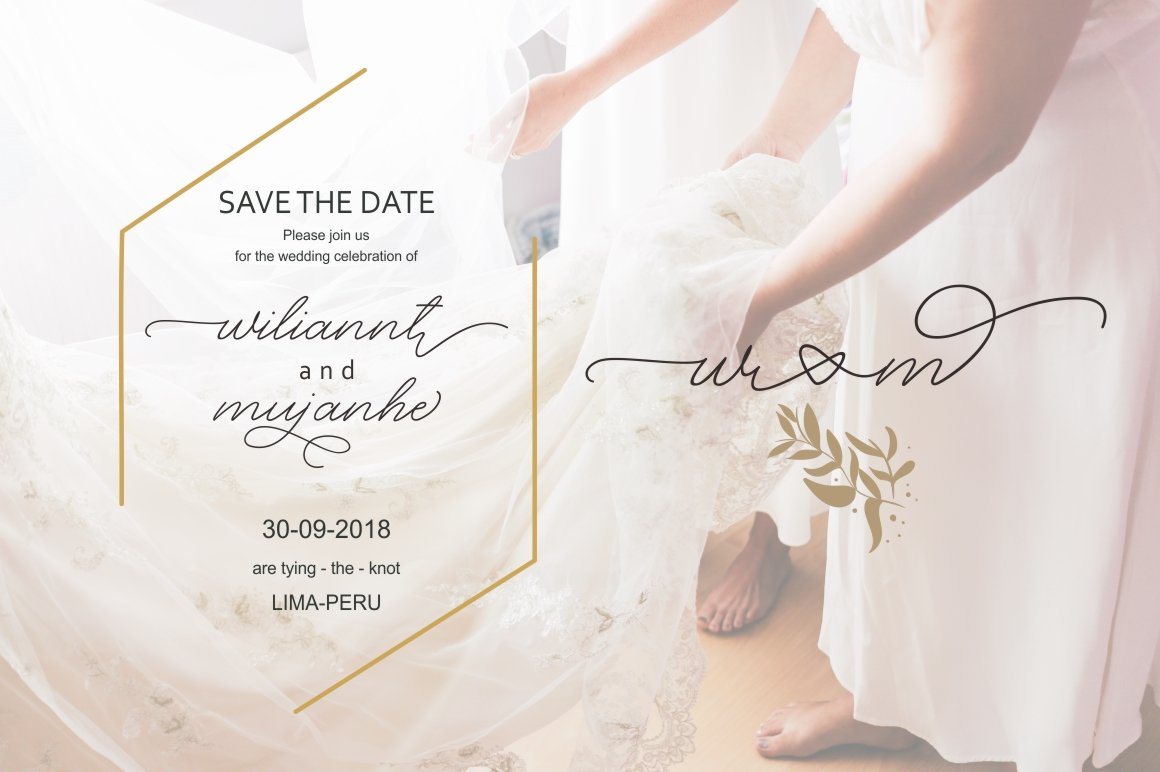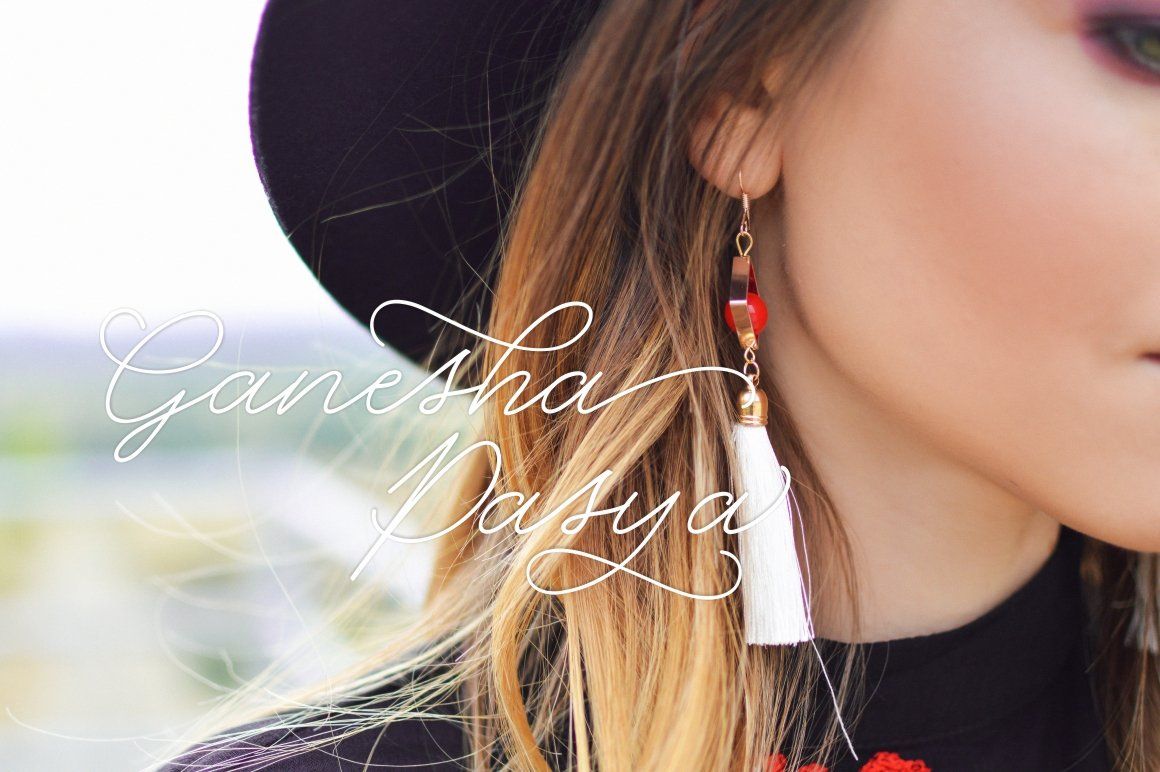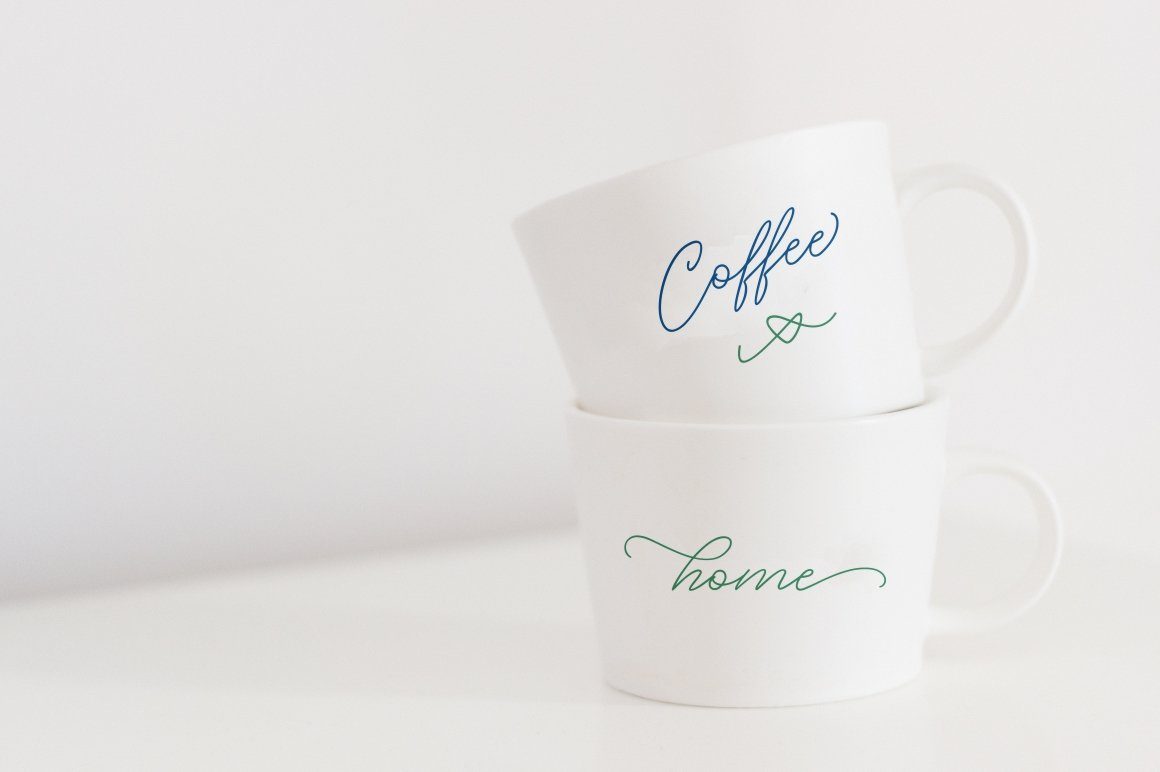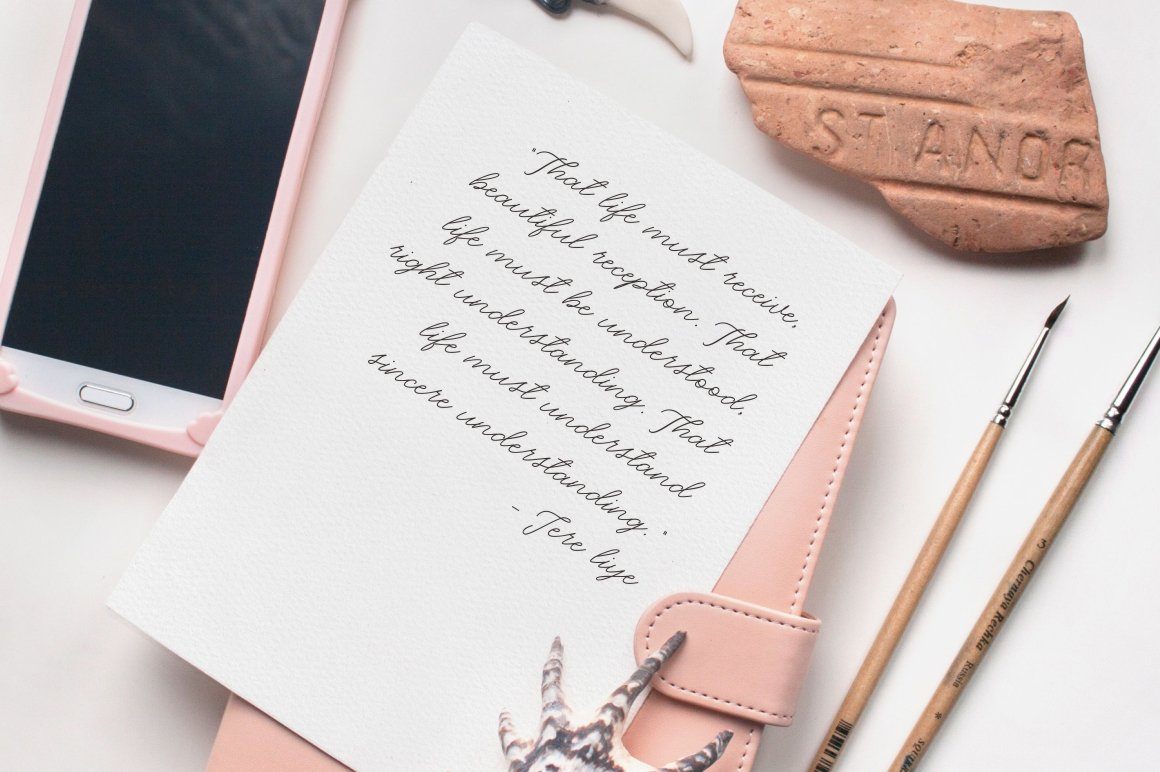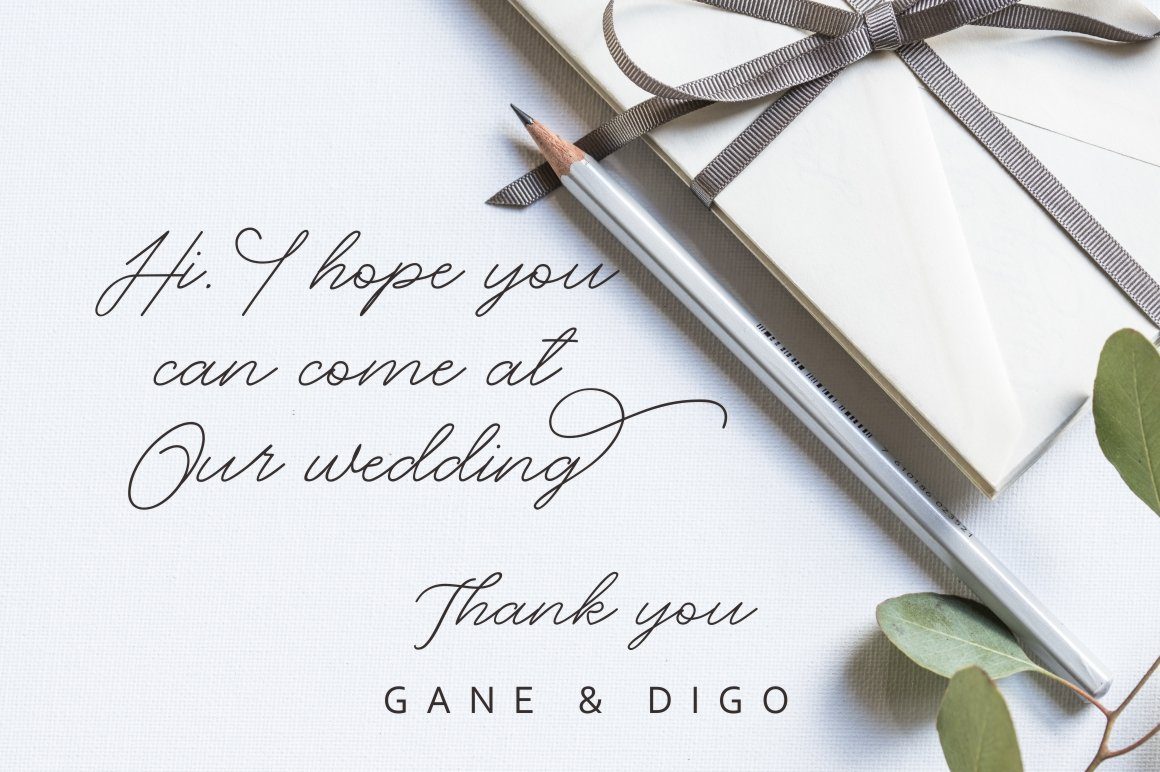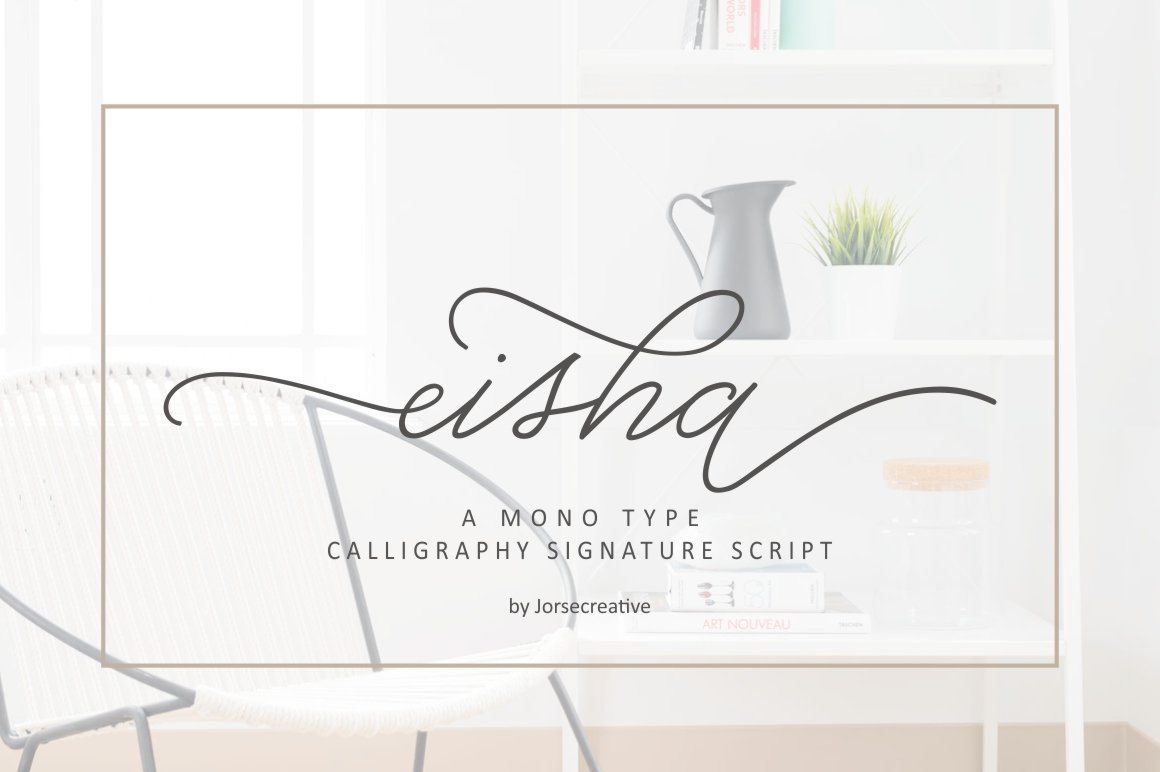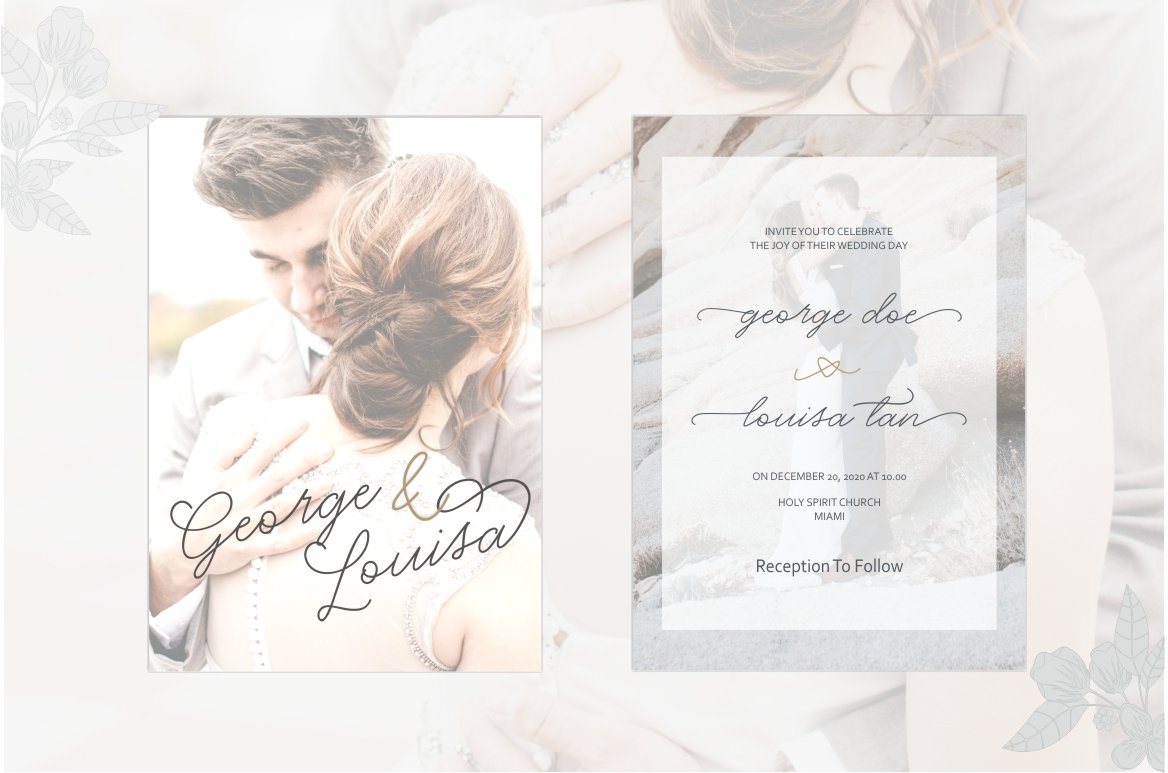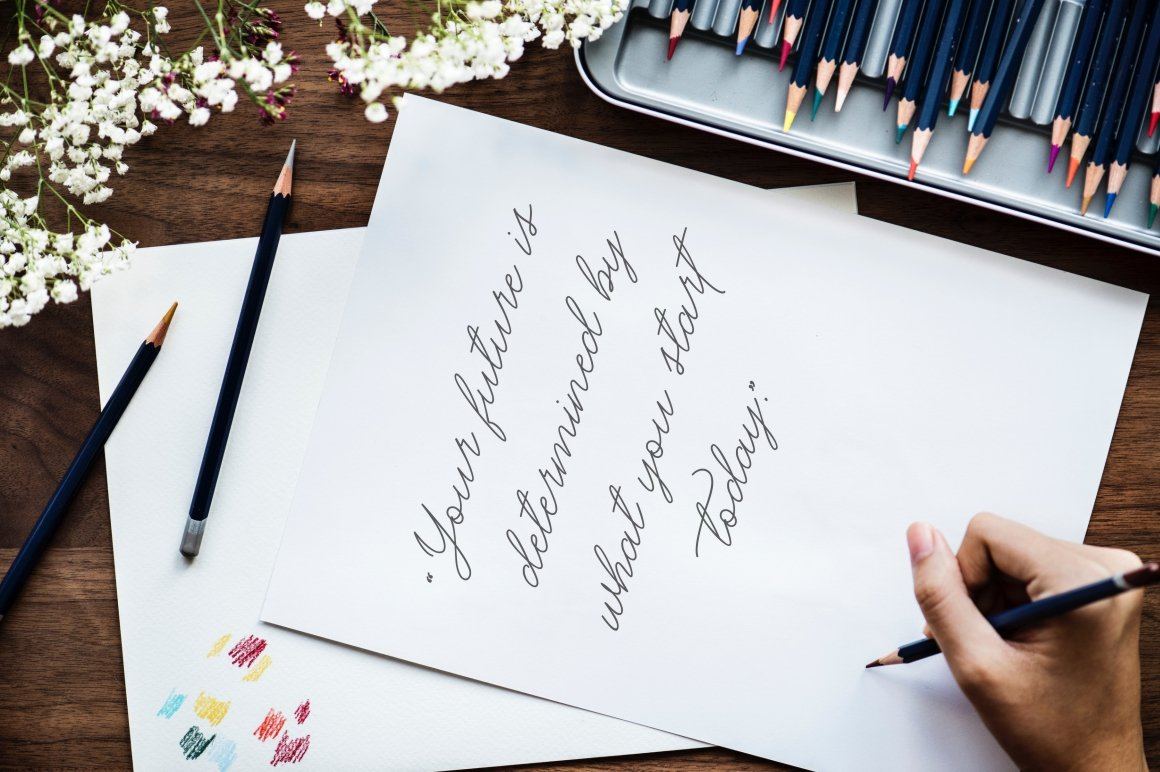
Eisha Script
About Eisha Script
Eisha Script adalah font kaligrafi modern dengan tulisan tangan dengan model mono-line, aliran yang canggih. Itu penuh dengan tarikan dan mesin terbang alternatif. Ini sempurna untuk branding, undangan pernikahan, buku harian, cangkir, mug, dan kartu ucapan . ‘Eisha Script’ includes a large set of beautiful capital letters and lowercase letters, multilingual symbols, numbers, punctuation and ligatures, in addition to standard ligatures as well as ‘a’ to ‘z’ ligatures to letters ‘s’ and ‘r’ more beautiful also includes an ampersand ‘&’ made in a love-like set of Stylistics options, which serves to connect two words or letters (It’s so perfect) The font has a smooth texture, so it will be perfect for all kinds of printing techniques and you can do embroidery, gold foil etc. The Features of this fonts is: Standard ligatures Discretionary ligatures Swash Alternates Stylistic sets PUA Unicode (Private Use Areas) You will get: Eisha Script OTF Eisha Script TTF Eisha Script EOT Eisha Script SVG Eisha Script WOFF To use a beautiful swash, you need a program that supports OpenType features like Adobe Illustrator CS, Adobe Photoshop CC, Adobe Indesign, and Corel Draw. Programs that support in this font is a Adobe Photo Shop, Adobe Illustrator, Adobe Indesign, Corel Draw and Microsoft Office.Languages supported: Breton, Catalan, Czech, Danish, Estonian,French, German, Hungarian, Icelandic, Italian, Romanian, Scottish Gaelic, Slovak, Latvian, Lithuanian, Norwegian, English, Finnish, Polish, Portuguese, Slovenian, Spanish, Swedish, Turkish, Welsh. Basically, all european languages that are based on latin alphabet Can be used for various purposes.such as headings, logos, wedding invitation, t-shirt, letterhead, signage, lebel, news, posters, badges etc. To enable the OpenType Stylistic alternates, you need a program that supports OpenType features such as Adobe Illustrator CS, Adobe Indesign & CorelDraw X6-X7. Basically, all european languages that are based on latin alphabet Can be used for various purposes.such as headings, logos, wedding invitation, t-shirt, letterhead, signage, lebel, news, posters, badges etc. To enable the OpenType Stylistic alternates, you need a program that supports OpenType features such as Adobe Illustrator CS, Adobe Indesign & CorelDraw X6-X7.